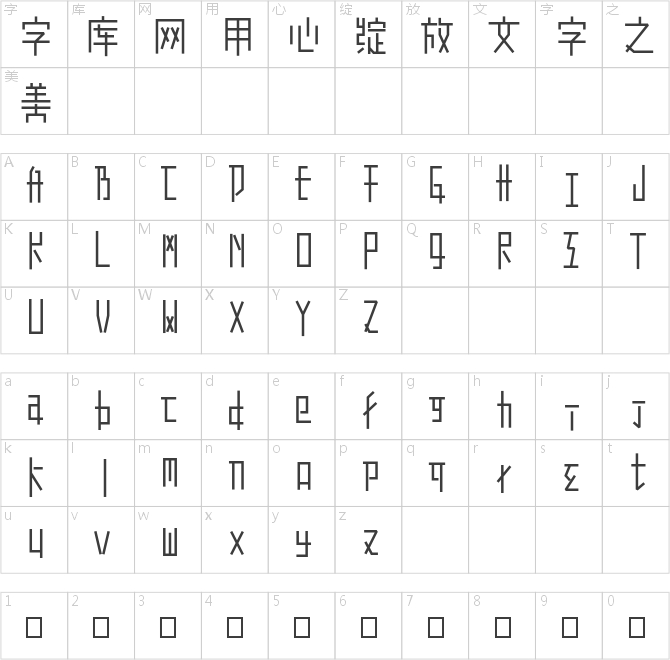
余繁真素體
余繁真素體介紹
上次說到要體系化字體的視覺平衡,花了將近四個月的時間才搞定。
現理論對于正字類字體還稍顯不足,但對簡單創意類字體是手拿把掐。
這個版本的真素體完全重制花了兩星期,對于把一個點子拓展成一個中文字體而言,這樣的時間開銷勉強算是可以接受了。
寫得跟數學書一樣的字形平衡理論估計在站酷沒幾人想看,單貼點圖看看具體效果哈。